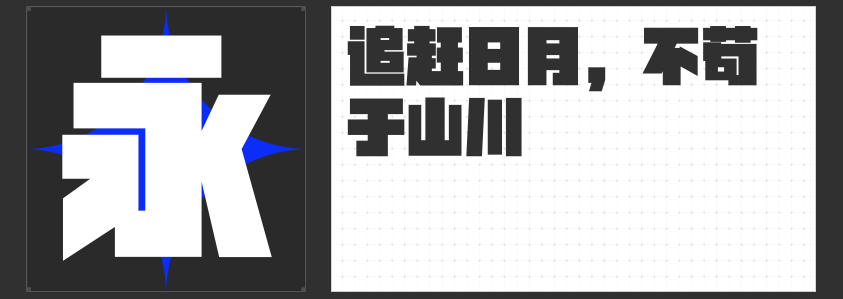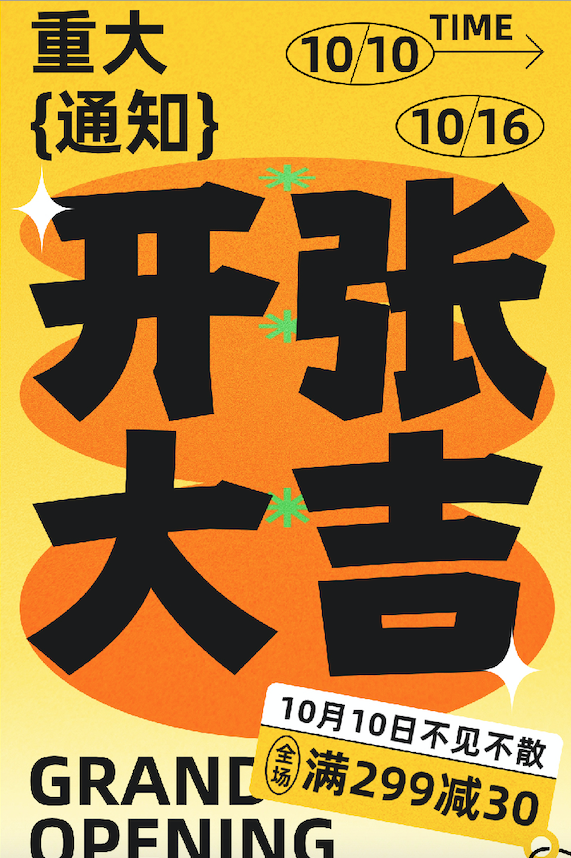
创意无限!四款黑体字体打造独特短视频标题
在短视频盛行的时代,一个吸引人的标题往往决定了视频能否在众多内容中脱颖而出。而一个独特的字体,则能让标题更加引人注目。今天,为大家推荐四款创意黑体字体,它们不仅各具特色,还能为短视频标题增添无限创意。
这款字体以其方正的字型和中宫较大的设计,让人一眼难忘。横平竖直、棱角分明的笔画特点,简约而不失力量。独特的去钩处理和竖直化的撇、捺、点,带来了强烈的镜像视觉效果。此外,励字开拓者系列化共5款家族字体,从正文到标题的平滑过渡,适用于各种场景。特别值得一提的是,这款字体还包含了诸如“叕”、“焱”、“㵘”等网红流行用字,让你的标题紧跟潮流。
这款字体巧妙地将中西设计手法结合,既展现了西文斜体装饰风格的浪漫优雅,又融入了汉字隶书笔画的韵味。倾斜112度的设计,使得字体充满动感,而蚕头燕尾的笔画变化,则赋予了字体独特的韵律感和节奏感。轻松明快的自洽节奏,让人在浏览标题时也能感受到一份愉悦。
这款现代创意型黑体,以其厚重的字型和略带开放性的设计,展现了强烈的现代感。笔画粗细不均等、横竖笔画梯形分布的特点,打破了传统黑体的认知。撇、捺、点中更多梯形元素的加入,使得整体风格偏硬而富有力量。这款字体无疑为你的短视频标题增添了一份独特的现代文艺气息。
4.高手兵克楷黑体
高手兵克楷黑体是一款值得一试的创意字体。其独特的楷书与黑体的结合,使得字体既具有传统韵味又不失现代感。
四款创意黑体字体,各具特色,总有一款能打动你的心。快来为你的短视频标题选择一款合适的字体吧!